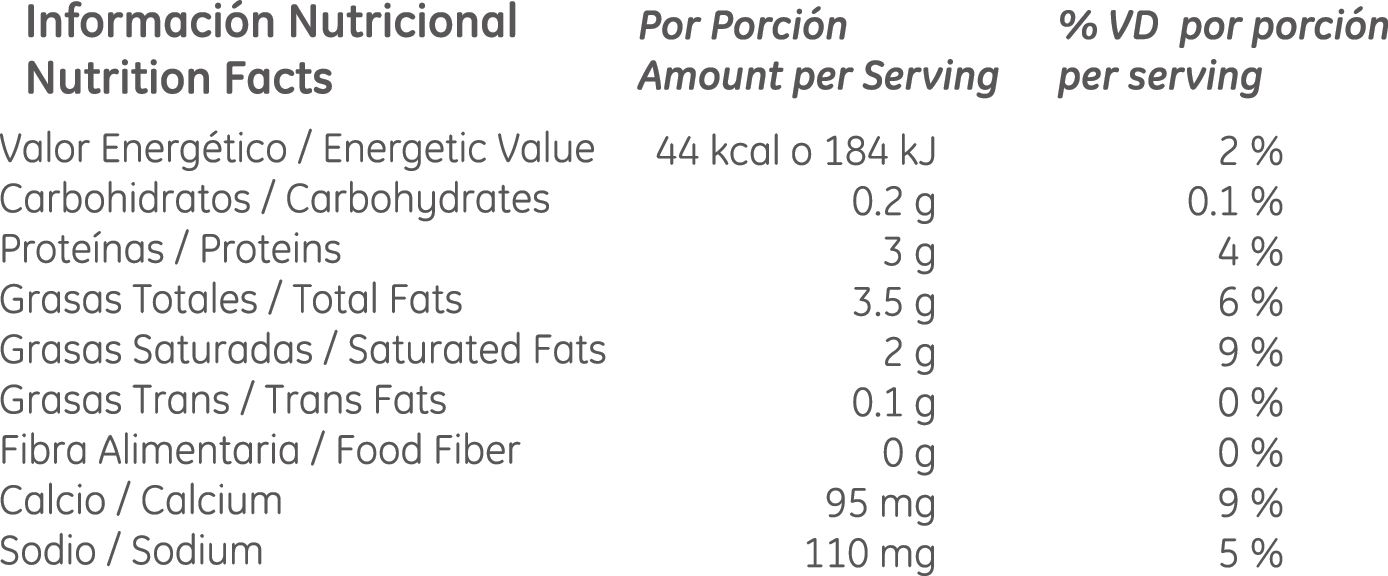
Foro de Tipografía Nombre de Fuente! el 19.09.2016 a las 14:07 por diegorossiok · 2 comentarios Seguir este tema Dejar de seguir este tema 2 seguidores Buen día, alguien puede decir el nombre de la tipografia? La Vag es muy parecida pero no es... Desde ya muchas gracias. Saludos. Comentar Me gusta
Creo estar seguro que se llama, GE Inspira.